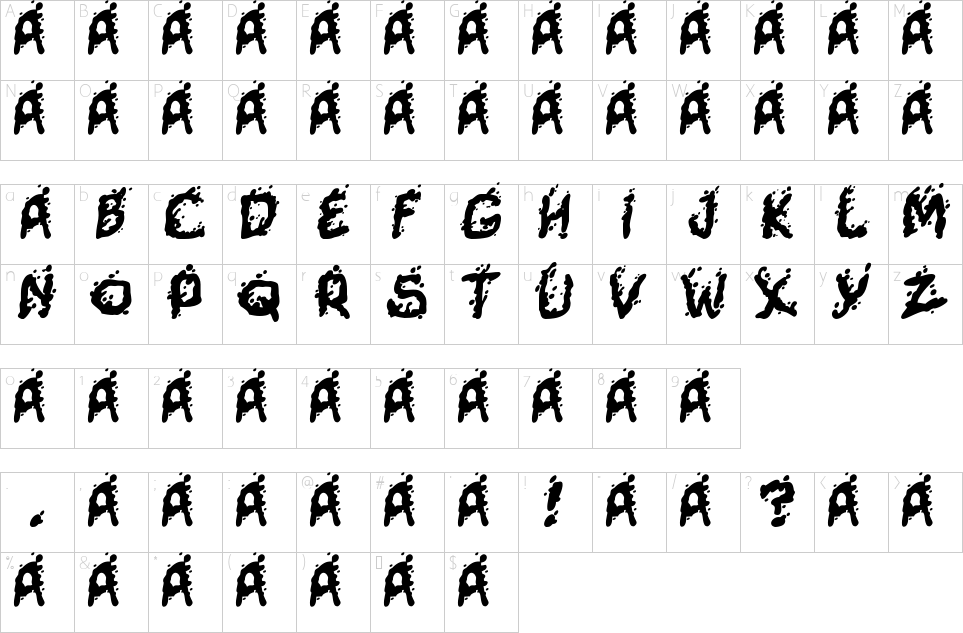
A Mutant Super Model é uma fonte única e audaz, ideal para quem procura algo que se destaque na tela. Desenvolvida pela Blambot Fonts, essa fonte surpreendentemente enriquece seu layout gráfico com um toque distinto e diferente. Com uma aparência vibrante e vibrante, ela é perfeita para estilos criativos e modernos. Esta fonte pode ser usada tanto no Windows quanto no Mac, permitindo que você personalize seus designs de maneira única. Com 1.963 downloads até o momento, é evidente que muitos designers já testaram e apreciaram o poder da Mutant Super Model. Sem dúvida, é uma fonte que vale a pena ser explorada, especialmente para quem busca algo um pouco diferente e inovador.